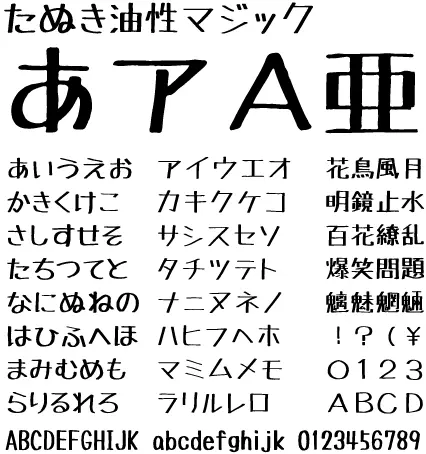
TanukiMagic(日文名:たぬき油性マジック)是用油性極粗線條在普通紙上寫的手寫文字製作的免費日語字體。收錄了平假名、片假名、英文數字、符號、JIS第二水準的漢字以及移位IBM擴展漢字。想用賀年卡和流行音樂等表現手寫風格的時候推薦使用,商務使用也可以免費自由使用。
普通紙に油性極太マジックで書いた手書き文字から作成した無料日本語フォントです。ひらがな・カタカナ・英數字・記號、JIS第二水準までの漢字及びシフトIBM拡張漢字を収録しています。年賀狀やポップなどで手書きっぽさを出したいときにお勧めです。 商用での利用も、無料でご自由にお使いいただけます。